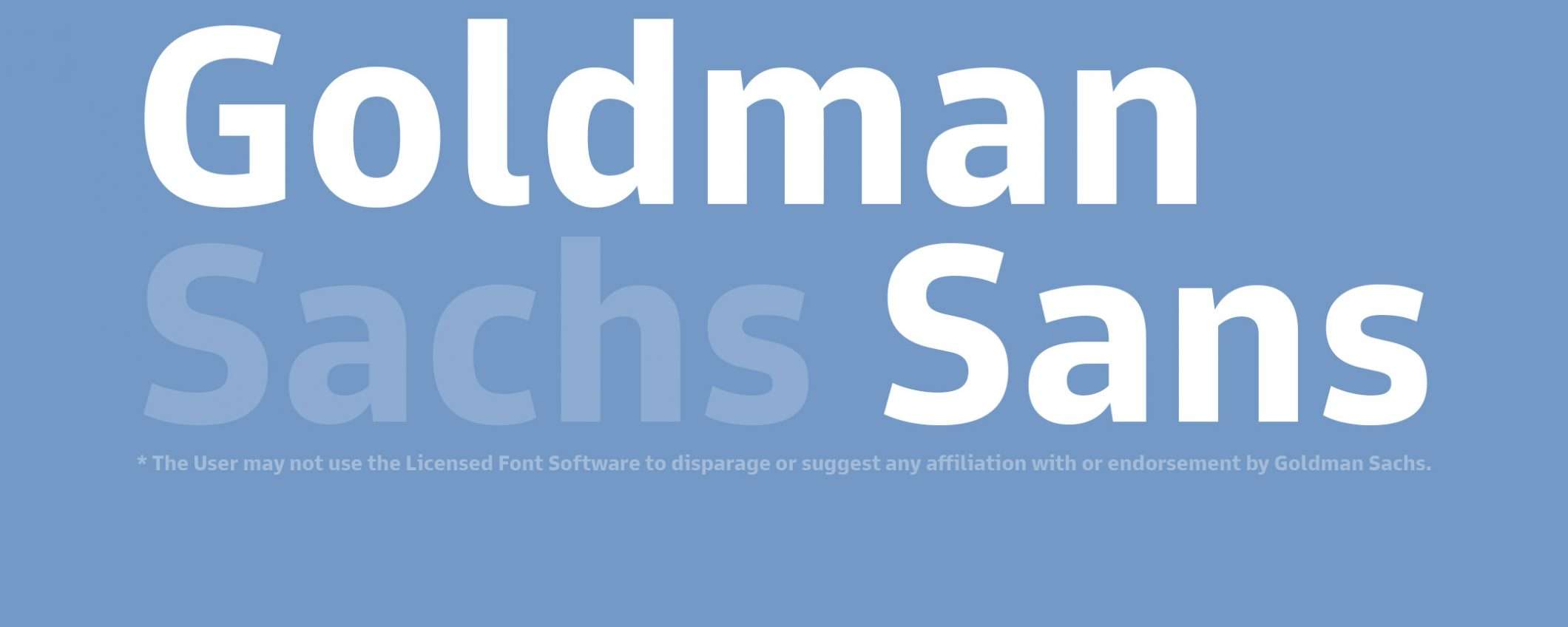
Dalla descrizione nella pagina di download si legge che “Goldman Sans è un carattere personalizzato progettato per le esigenze della finanza digitale”. Insomma, un font, offerto per l’utilizzo libero e gratuito da Goldman Sachs, una realtà che in tempi recenti ha puntato sempre più sull’ambito FinTech attraverso iniziative come il coinvolgimento diretto nel progetto Apple Card.
Goldman Sans: il font di Goldman Sachs
Nulla di particolarmente eclatante, se non fosse per un passaggio dei termini di utilizzo in cui si mette nero su bianco che è proibito “utilizzare il font per denigrare e suggerire alcuna affiliazione o endorsement di Goldman Sachs”. Già, cosa potrebbe andare storto?
Non è trascorso molto prima che i social si riempissero di post come quelli allegati qui sopra e sotto, prendendo di mira la banca d’affari con riferimenti all’attività del gruppo e testi scritti ovviamente proprio utilizzando il carattere in questione.